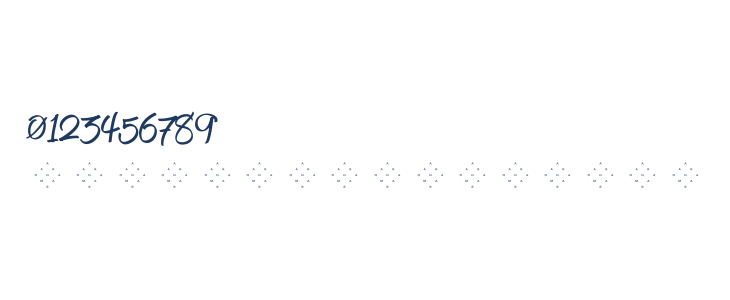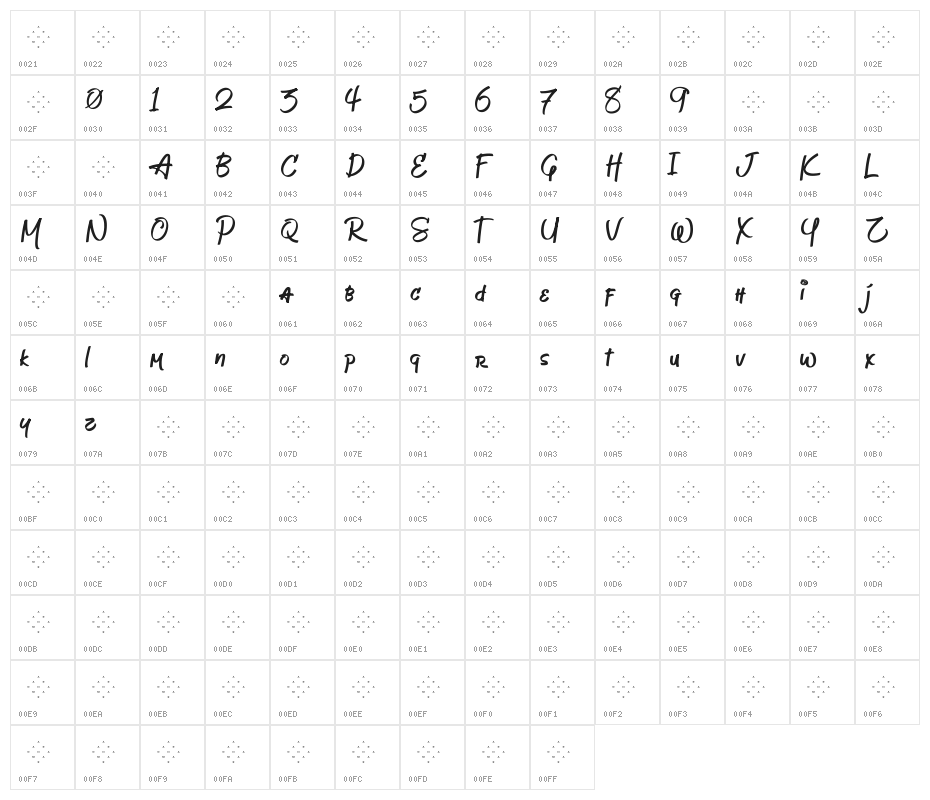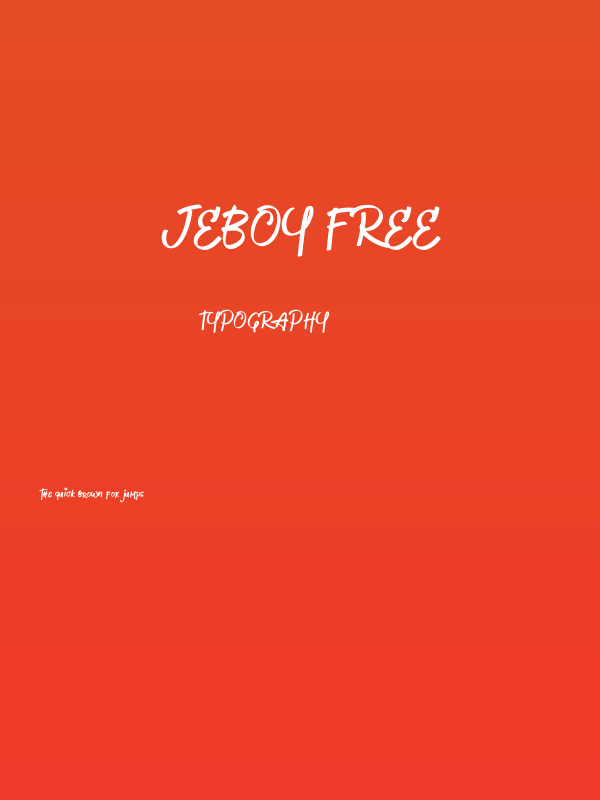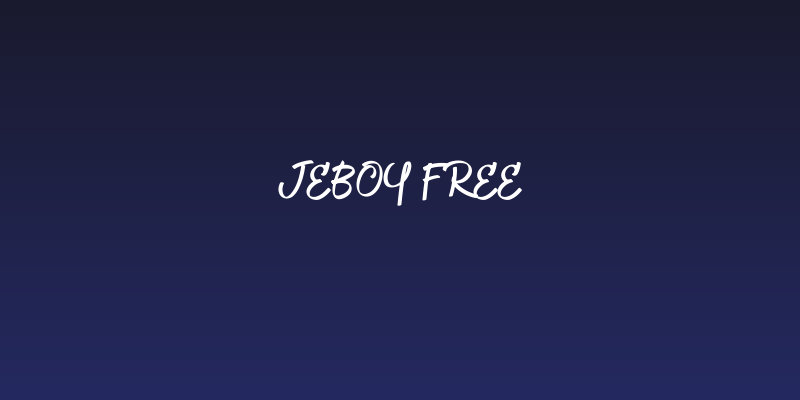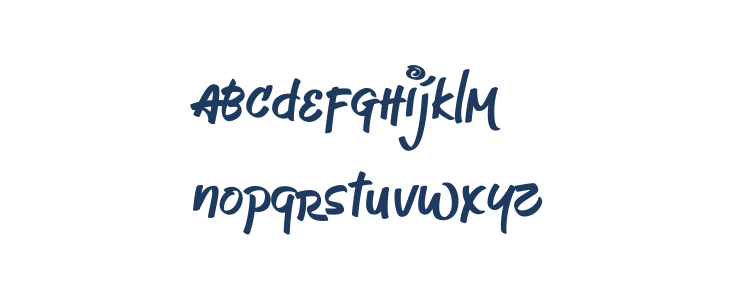
Jeboy Free Font
| Caso d'uso | Headlines, Logos, Invitations |
| Progetti proposti | Ideal for creative projects such as invitations, greeting cards, posters, and branding materials that require a personal and artistic touch. |